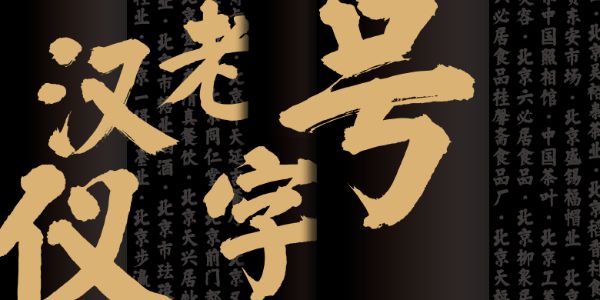
从古代穿越而来的招牌字体
书写字体
汉仪老字号是由汉仪字库签约作者半屋创作的一款榜书书法字体。这款字体沉稳端庄、气势恢宏,适用于海报、招牌、 影视、书籍等多种场景。
榜书又称大书或大字,最早被用作官府宫殿的牌匾题字。从秦汉发展至今,榜书已有数千年的历史。唐以后,颜真卿的书法给后世榜书的风格带来了深远的影响。榜书的风格大气庄重,早在北宋时期就已经被用来题写商业招牌,广泛使用。
时至明清,各家店铺都非常注重店名招牌,更有店铺请名人题写匾额用以宣传,借着“名人效应”宣传自己,树立店铺形象。这种请名人题写匾额的习俗流传至今,人们耳熟能详的众多老字号都保留了名人笔墨。
在台北街头,楷体字的招牌随处可见,而且往往是颜楷,颜楷厚重端正的风格是儒商精神的具象(参考《字形散步》,柯志杰、苏炜翔著)。在老式手写招牌式微的今天,汉仪老字号或许可以成为招牌字体新的选择,传达厚道、诚信的经营理念。
汉仪老字号的书写取法颜真卿,重心偏高,结构平稳密实,笔画气势磅礴,笔力遒劲。继承了传统榜书中正、端庄之势的同时,又保留了丰富的笔墨细节,因而更具表现力与视觉冲击力,有声量大、细节足的特点。
苏轼曾在《论书》中有言:“大字难于结密而无间,小字难于宽绰而有余。”汉仪老字号的字面较大,中宫外扩,黑多白少,结字严密。在实际应用场景中,既可以通过宽博的字形做到迅速抓人眼球,又可以凭借平稳的气质避免对观者的过度打扰。
汉仪老字号在书写过程中力图做到“稳中求变”,在整体结构趋于平稳的基础上,制造笔画疏密、粗细、空间分布的节奏与变化,避免千篇一律。更加贴近手写的原貌,在阅读时富有趣味。
汉仪老字号的笔画粗黑有力,笔锋藏而不露,笔画直中带曲,富有弹性。坚韧的长笔与浑圆、厚重的点画,为整个字形塑造了精神饱满的姿态。
勾、挑干脆利落,配合少量牵丝与飞白,暗示笔画间的连带关系,字形静中有动,为这套整体风格较为平稳的字体增添了节奏与活力。
汉仪老字号的横画向右上角倾斜角度较大,左紧右松呈喇叭口状,向右上方打开,符合执笔书写时的手势,同时充满气势,富有张力。
相比传统榜书牌匾上刻制而成的平滑轮廓,汉仪老字号笔画中保留的墨痕为字体增添了丰富细节,最大程度保留了手写的痕迹,在视觉感受上拉近了与观者之间的距离。
西文部分延续了中文笔画的书写方式,同样保留了丰富的笔墨细节,厚重饱满、气势十足。在保证整体和谐的同时,继承了中文笔画中的手写感与节奏变化,颇具风格。在与中文搭配使用时能做到和谐统一,相互照应。